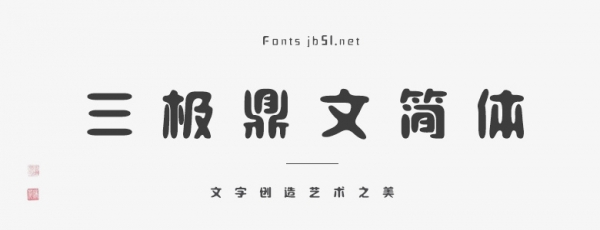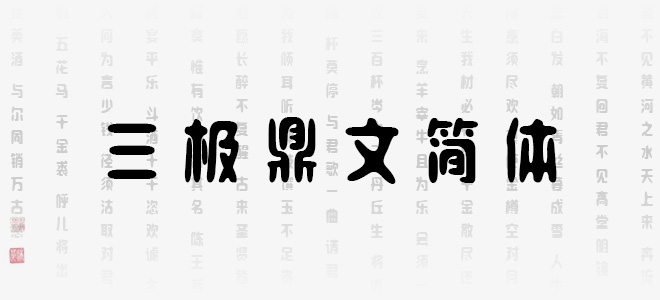
三極鼎文簡體創(chuàng)意源自鑄刻于鐘鼎之上文字,筆道肥粗,彎筆多,團塊多。筆畫由粗細相參而趨于均勻劃一;收筆與起筆為圓筆;字形端正,端整之中又有流麗之風(fēng)。其以曲線為主,間架平穩(wěn),整齊中寓變化,氣勢奔放,特點明顯。適用于少兒類讀物、書刊、品牌廣告、文化用品包裝設(shè)計以及社交網(wǎng)絡(luò)個性化用字。
三極鼎文簡體